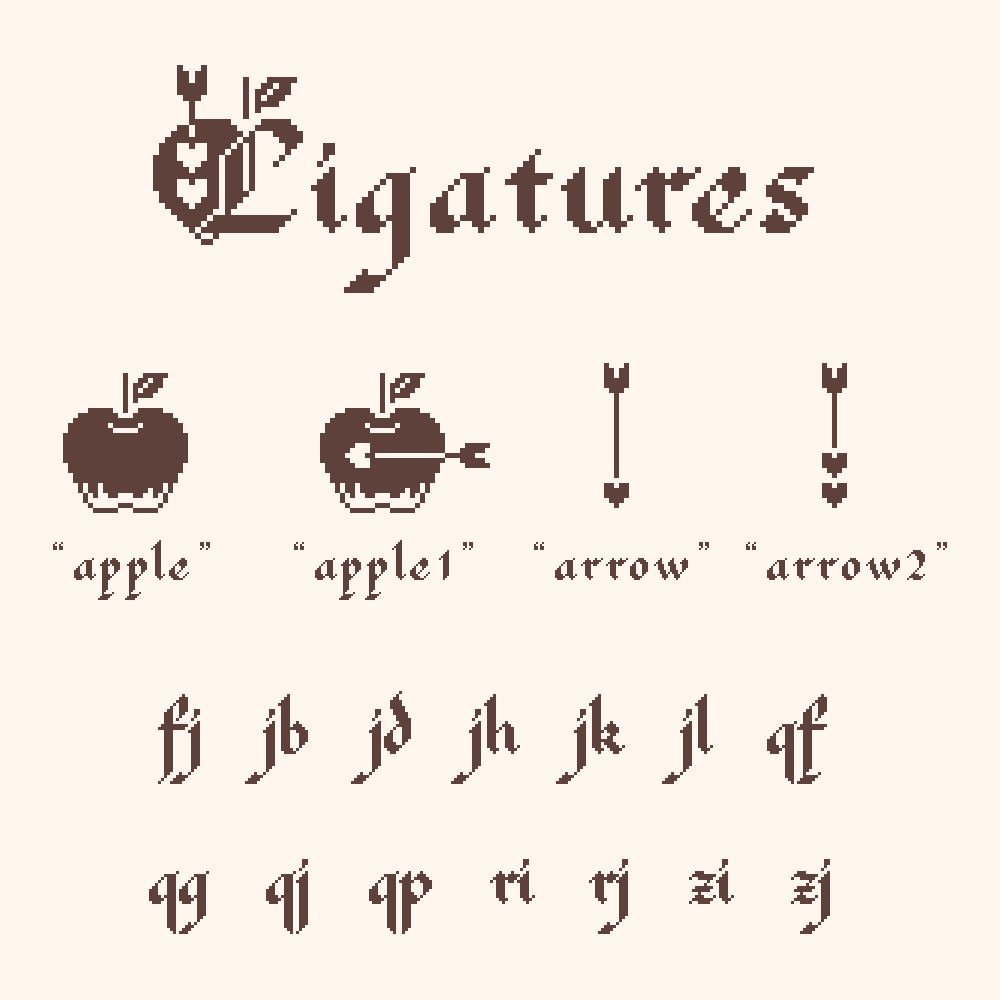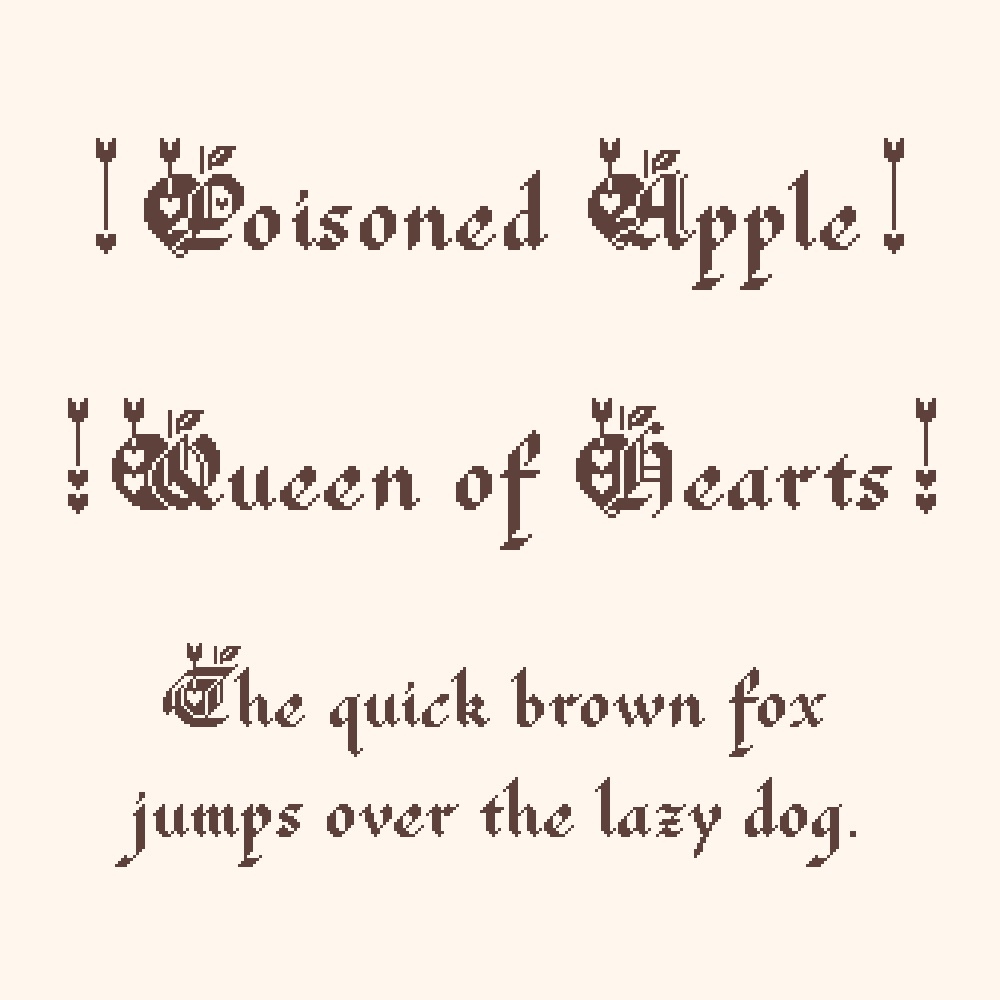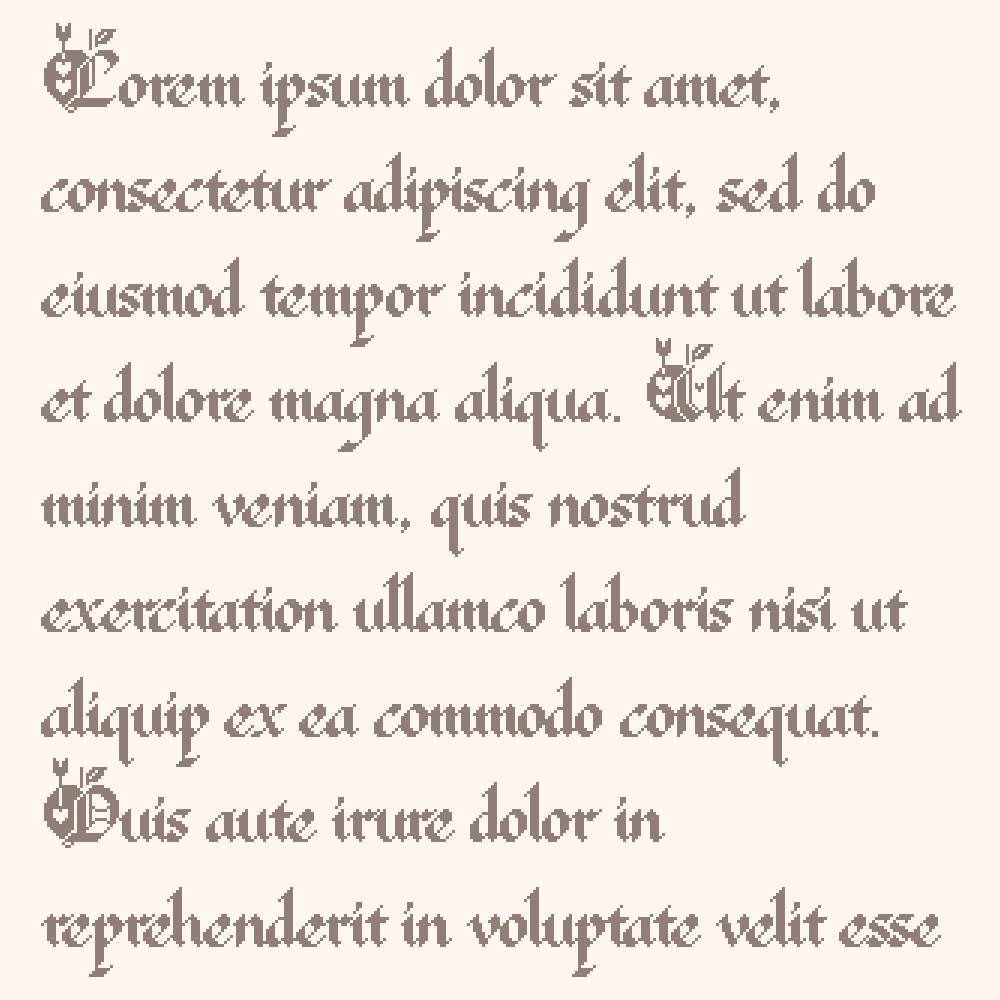
Cdot-Apple(フリーフォント)
フォント「Chamed」のドットバージョンです。 「シードットアップル」と読みます。 英数字とリガチャが少し入っているOpenTypeフォントです。 ★このフォントについて詳しい使い方はこちら https://satsuyako.com/cdot-apple/ ★利用規約はこちら https://satsuyako.com/license-agreement/ ↓元ネタのChamedはこのフォントです。 https://satsuyako.booth.pm/items/4801638 他にもフリーフォントを配布しているのでよかったら見てください! https://satsuyako.com/category/free-fonts/